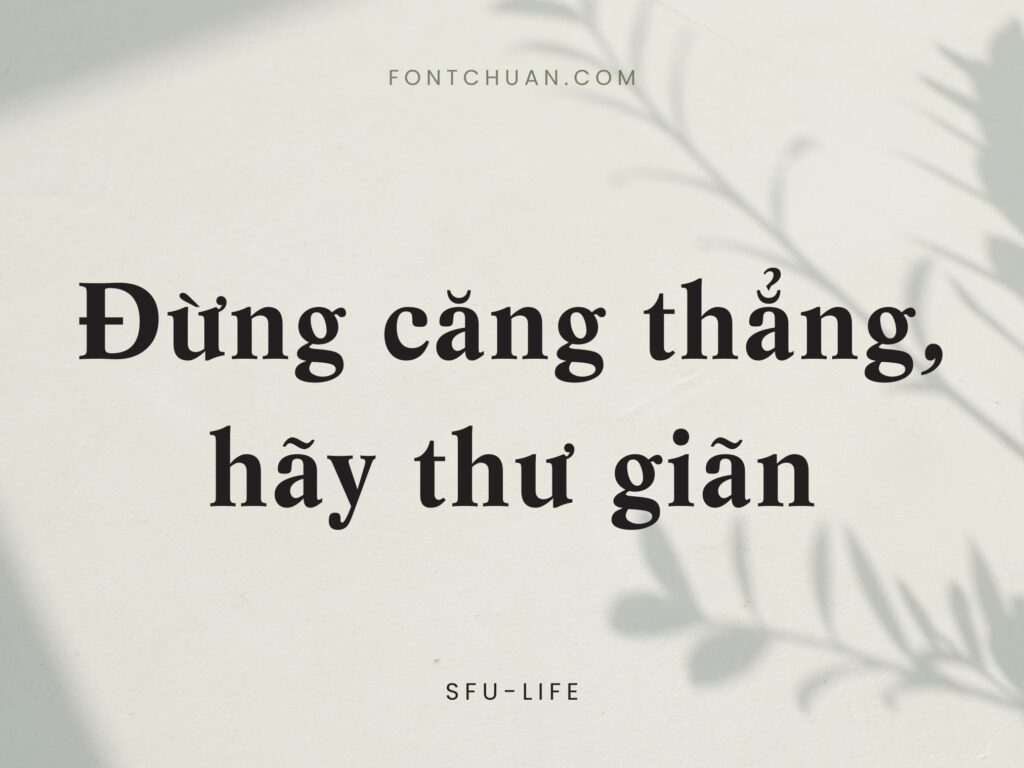
Life là một kiểu chữ serif chuyển tiếp (Transitional serif) được thiết kế bởi W. Bilz và Francesco Simoncini cho nhà đúc chữ Ludwig & Mayer vào năm 1965. Font này được sưu tầm và đăng bởi thành viên của Font Chuẩn. Life được biết đến như một kiểu chữ cổ điển thường được sử dụng trong các tờ báo, nhưng cũng là một lựa chọn tuyệt vời cho web. Với thiết kế tinh tế và độc đáo, Life không chỉ phù hợp làm Font logo cho các thương hiệu cần sự trang trọng mà còn có thể ứng dụng hiệu quả như một Font chữ quảng cáo trong các chiến dịch truyền thông hiện đại.
Về mặt thiết kế, Life có các đường nét gọn gàng, tỷ lệ cân đối và độ tương phản cao, tạo cảm giác thanh lịch và chuyên nghiệp. Font này hỗ trợ nhiều ngôn ngữ và bao gồm các ký tự đặc biệt, giúp người dùng dễ dàng tùy chỉnh theo nhu cầu. Life thường được sử dụng trong các thiết kế đồ họa, in ấn, biển hiệu và nhận diện thương hiệu. Các ngành nghề như quảng cáo, công nghệ, giáo dục và bất động sản có thể tận dụng kiểu chữ này để tạo dấu ấn đặc biệt trong truyền thông.
Đặc biệt, trong những thiết kế mang tính tri ân và tôn vinh, Life có thể ứng dụng làm Font ngày Nhà giáo Việt Nam để tạo ra các ấn phẩm mang tính trang trọng, hiện đại nhưng vẫn giữ được sự gần gũi và ý nghĩa sâu sắc.